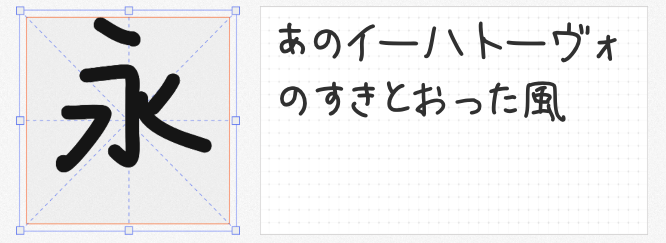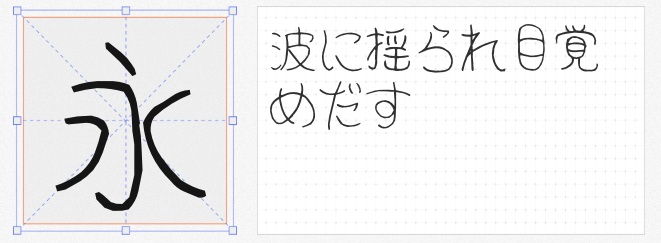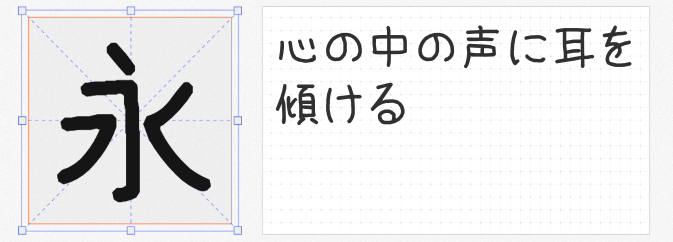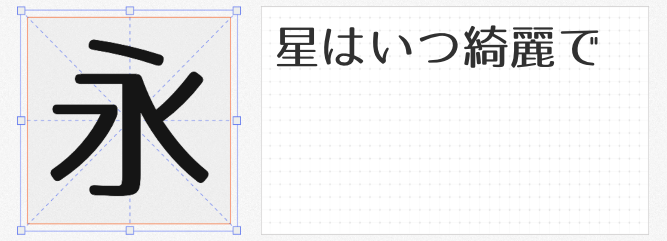
四款治愈系日系手写字体推荐:免费商用打造萌趣设计
在追求设计个性化的今天,日系手写字体以其独特的可爱风格成为设计师的心头好。本文精选四款可免费商用的日系手写字体,为你的作品注入灵动与温度。
1. ほにゃ字 ver.Re
由日本设计师铃木るいち创作的ほにゃ字 ver.Re,以灵动笔触赋予每个汉字生命力。这款字体支持中日韩统一表意文字、基本拉丁文及符号,笔画转折处充满自然弧度,仿佛孩童稚嫩的笔迹。其授权方式为作者声明,个人与企业均可免费商用,适用于儿童品牌包装、手账模板或社交媒体表情包设计,传递轻松愉悦的视觉感受。
2. 壹城劳拉手写体
以虚拟主播壹城劳拉手写字体为蓝本的这款字体,完美复刻了日系少女的俏皮笔触。它覆盖JIS汉字标准、平假名、片假名及部分西里尔字母,字形圆润中带有一丝慵懒,适合用于咖啡馆菜单、文创周边或短视频标题。需注意,作者保留著作权,禁止二次分发,但允许免费商用并鼓励向作者报备使用案例。
3. 日系LOGO黑体
基于M+字体调整的日系LOGO黑体,突破传统黑体的刻板印象。其笔画粗壮却保留圆润收尾,兼具力量感与温柔气质,特别适合母婴品牌、甜品店LOGO或活动主视觉设计。
4. Maru berry字体
由日本设计师軽缶创作的Maru berry字体,以手写原稿为基底,保留了纸面摩擦的质感。其字形饱满圆润,笔画粗细变化自然,尤其适合手账本封面、绘本插画或手作品牌包装。该字体采用作者声明授权,允许免费商用但禁止修改,建议用于需要传递温暖氛围的设计场景。
四款字体均支持中日双语设计,但需注意:ほにゃ字 ver.Re与Maru berry字体在简体汉字覆盖率上存在局限,建议优先用于标题或装饰性文字;日系LOGO黑体则更适合需要高辨识度的LOGO或标语。
让这些充满童趣的日系手写字体,为你的设计增添一抹治愈色彩吧!